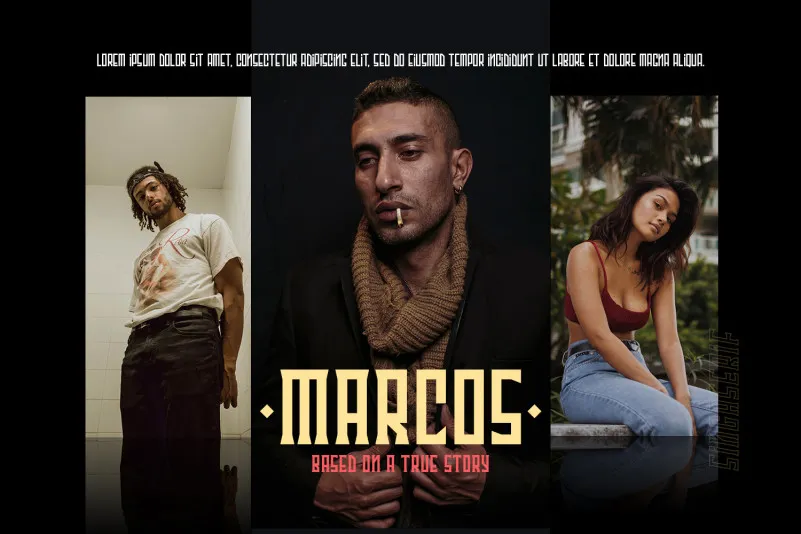
Singa Typeface – Download Grátis
A fonte ‘Singa Typeface’ é uma família de tipo clássica casual com três estilos distintos. Ela vem embalada com 9 pesos variáveis que permitem diferentes níveis de destreza e elegância na escrita, tornando-a perfeita para uso em diversos ambientes – seja um site profissional ou um cartão personalizado. Com ‘Singa Typeface’, o designer madeDeduk oferece uma fonte versátil, adequada a todos os estilos desde clássicos até contemporâneos. Este conjunto de peso variável não apenas adiciona profundidade ao texto, mas também permite que você personalize a aparência da sua identidade visual para destacar seu estilo único. Uma opção ótima para designers, especialistas em design gráfico ou qualquer um que deseje adicionar uma textura única à sua criação.